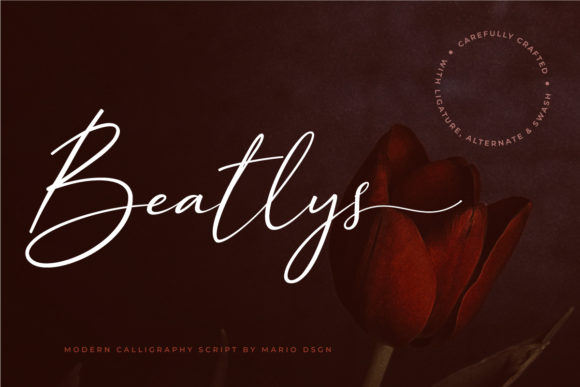
Beatlys - это современный каллиграфический шрифт, имеющий чистую, тонкую и гладкую вибрацию.
Beatlys идеально подходит для проектов по созданию логотипов и брендов, дизайна свадебных приглашений, фотографии, моды, рекламы, этикетки и упаковки продукции, водяных знаков и других проектов, которые нуждаются в рукописном и фирменном стиле.